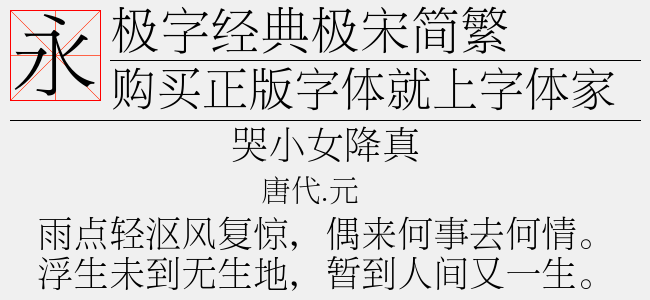
极字经典极宋简繁-极字和风字库
极字经典极宋简繁是一款大小2.21 M的极字和风字库字体,主要特征是宋体,印刷,内文,公文,,极字经典极宋简繁为TTF格式的文件,采用安装嵌入,包含了英文、拉丁文以及日文等符号,字宽中等(正常),当前版本是Version 1.000,共计6763个汉字以及附加其他英文字体和阿拉伯数字。
字体作者:极字和风字库
字体名称:极字经典极宋简繁